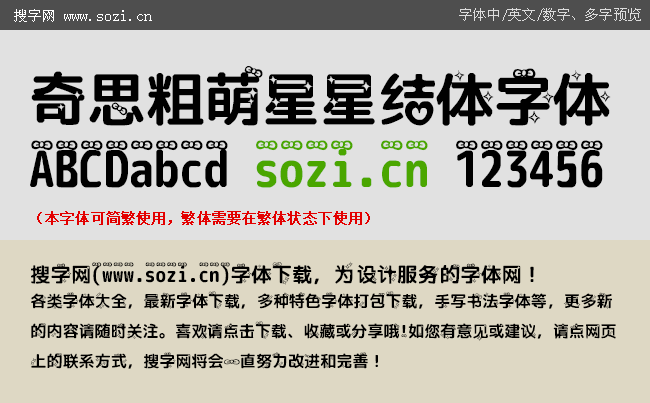
奇思粗萌星星結(jié)體字體
搜字網(wǎng)給大家提供一款奇思粗萌星星結(jié)體字體手機(jī)中文字體下載。這款手機(jī)字體是以粗圓字體為原形,字體間嵌入了可愛的卡通星星與蝴蝶結(jié)圖案。在具備粗圓字體清晰醒目風(fēng)格的同時,卡通味也特別濃,是一款非常可愛的卡通字體,特別適合喜歡手機(jī)字體個性一些的朋友在手機(jī)上安裝使用。